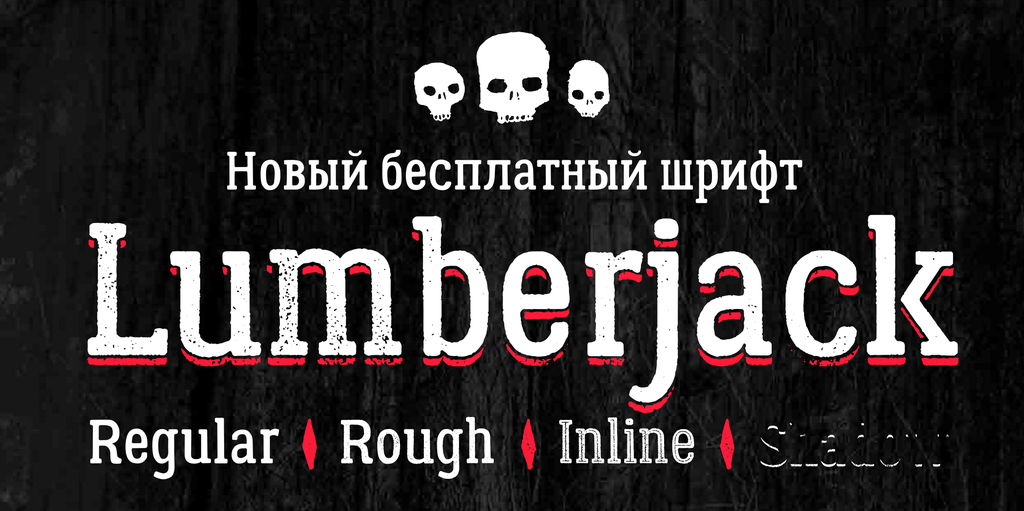
Lumberjack Font Family – Fonte Grátis
Lumberjack Font Family
Esta coleção de fonts gratuitas foi criada por designers que desenhou esses tipos e permitiu ao público usar, compartilhar, modificar e melhorar a fonte sem custo algum. Quer seja designer ou não, você pode participar dessa iniciativa benéfica com seu dinheiro — em nome do amor. Toda a arrecadação será destinada à tratamento de crianças com câncer. A fonte Lumberjack é uma serif que captura o espírito descontraído e criativo dos designers. Ela combina elementos dinâmicos e legíveis, ideal para uso em materiais educacionais, sites profissionais ou até mesmo como fontes de design de moda. Se você adora a maneira como essa font foi criada, participe com um gesto solidário e contribua diretamente para crianças que precisam disso. O projeto é uma bela forma de fazer o bem enquanto experimenta novas ferramentas de gráfica e ajuda a melhorar o impacto na vida dos pacientes de câncer. Não perca essa oportunidade única de criar algo mais além do design, contribuindo com um pouco para beneficiar outras pessoas que precisam.